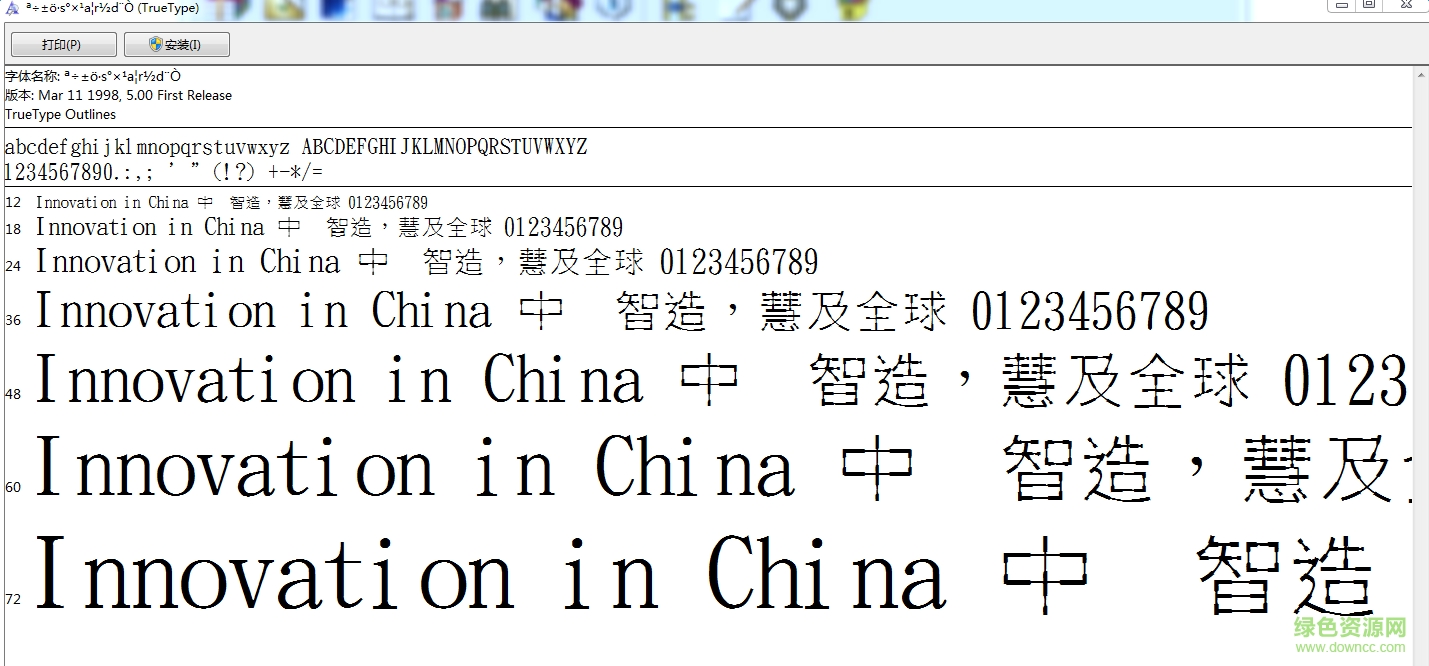
金梅新啞鈴字范例字體是一款金梅范例字體軟件,金梅類的字體給人非常正式的感覺,深受廣大年輕人的喜愛,還有更多好看字體盡情期待,歡迎到綠色資源網(wǎng)下載體驗!
金梅新啞鈴字范例是一款金梅范例字體,效果比較黑,喜歡金梅體字的朋友可以下載使用看看效果如何。
如果從設(shè)計的純角度來講,運用的也是非常少的。筆畫很均勻并且撇撩筆畫不尖,使人易于閱讀。由于其醒目的特點,常用于標(biāo)題,導(dǎo)語,標(biāo)志等等。當(dāng)然常見的標(biāo)題、導(dǎo)語采用的是方正字庫里的粗黑,大黑,中黑,而不是我們WINDOWS里自帶的。
與比較相似,只是比還要細(xì),常用于時尚雜志的正文,與筆畫橫平豎直、結(jié)構(gòu)醒目嚴(yán)密、便于閱讀,所以時尚雜志中比較常見,當(dāng)然,這一類字體不適宜在報廣(報紙廣告)的文字選擇,因為報廣印刷粗糙,細(xì)黑幾乎無法識別,但是在印刷精美的一些時尚雜志中,細(xì)黑與細(xì)等線會表現(xiàn)的非常精美。